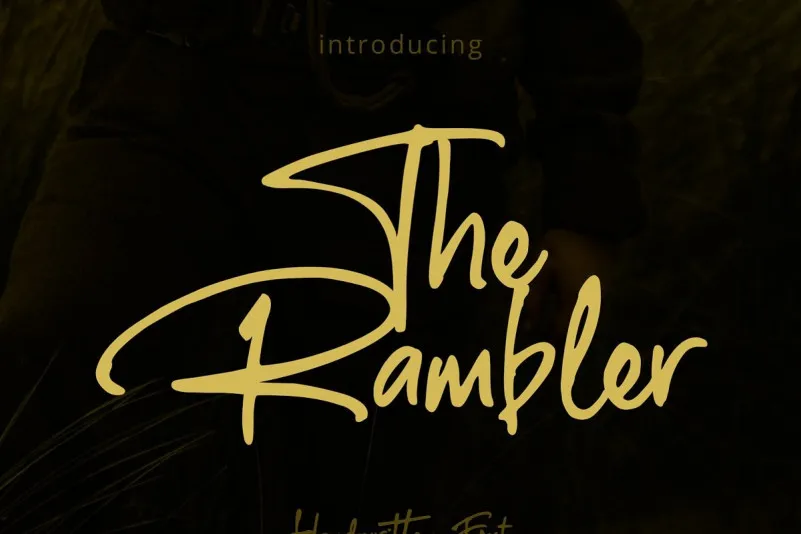
The Rumbler Script Font – Download Grátis
Introduzimos The Rumbler Script Font. Esta é uma elegante script font moderna. Ela possui um visual clássico, elegante e contemporâneo. Foi criada pela equipe do GemesFont. Você receberá esta bela fonte de script. Esta fonte está disponível com várias swirls modernas que podem fazer seu trabalho parecer elegante, suave e perfeito. Pode ser usada para um vasto conjunto de finalidades, como cartazes, convites de casamento, marcas de marca, assinaturas, logotipos, camisetas personalizadas, rótulos, avisos, posters e muito mais.